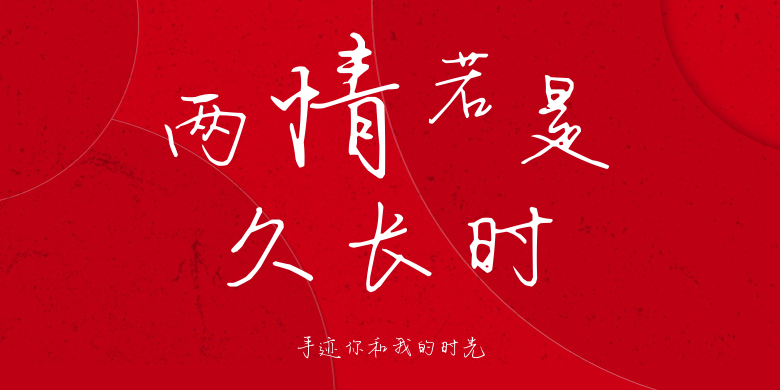
手迹你和我的时光
手迹你和我的时光,这款字体结构工整、笔画清晰,兼顾美观与易读性,适用于标题、正文、海报、包装、LOGO 等多种场景。字形优雅稳定,风格百搭耐看,适配日常排版与创意设计,让文字呈现更舒适、更具质感。手迹你和我的时光一笔一画,皆是细节,以均衡的比例、流畅的线条打造舒适视觉体验,字形端正大气,风格简约现代。无论是商业设计、品牌宣传还是日常排版,都能轻松驾驭,让文字更有格调与力量。手迹你和我的时光字体下载。